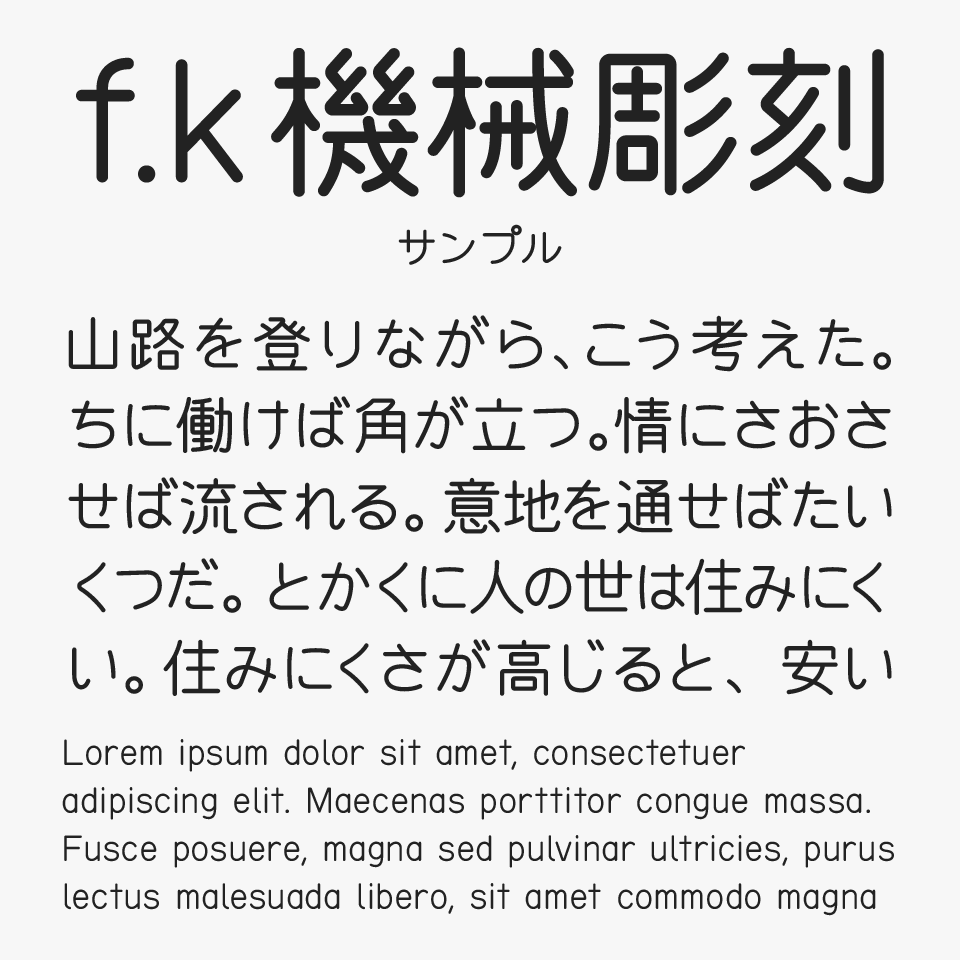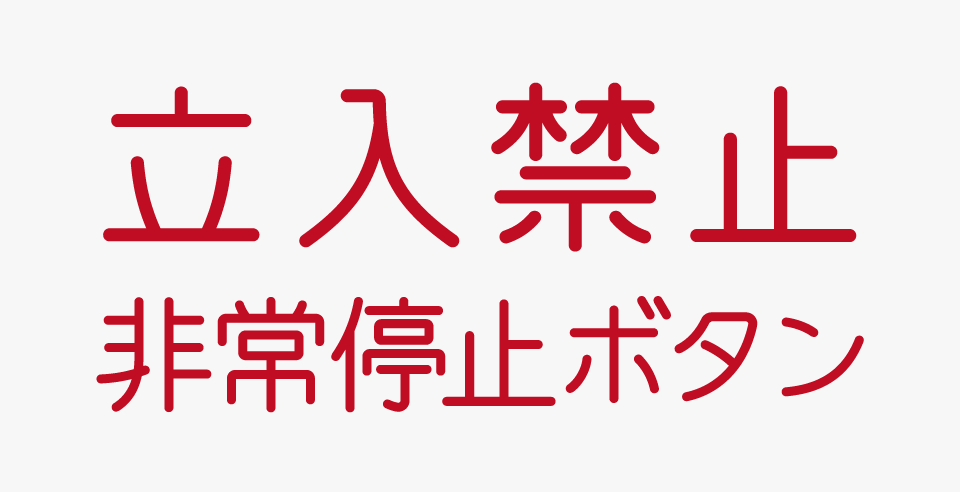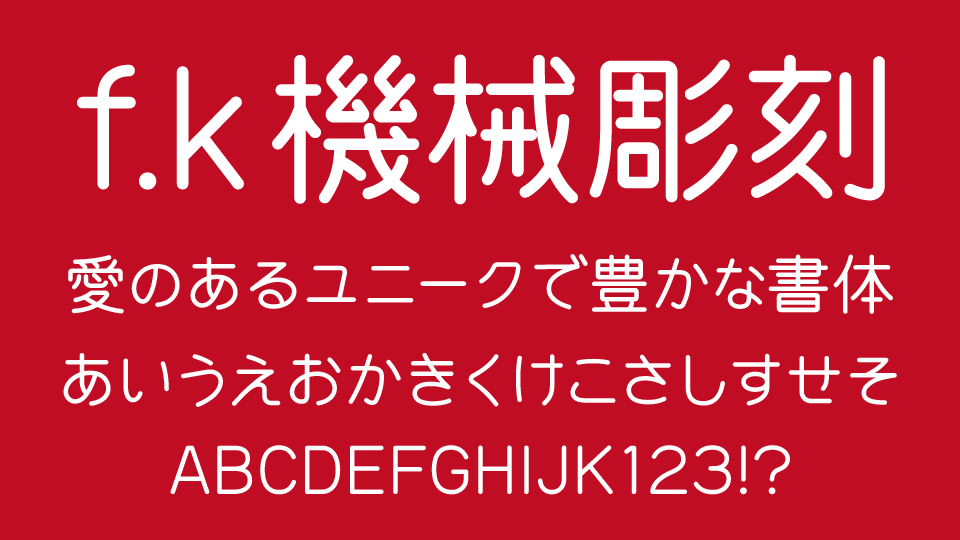
機械彫刻用標準書体(f.k 機械彫刻)フォントは、日本産業規格(JIS/旧日本工業規格)によって定められている、工業用途向けの標準書体をデジタルフォント化したフォントです。
均一で無駄のない線設計になっており、どこか無機質で工業的な雰囲気があるところが特徴のフォントです。視認性を重視して設計されているため、シンプルながら独特な存在感があり、インダストリアル系デザインやテクニカルなビジュアルとも相性の良いフォントとなっています。
駅のホームにある案内表示や看板、歩道橋、公共施設のサインなどにも多く使われている書体のため、意識していなくても、一度は目にしたことがある方も多いかもしれません。日常に溶け込んでいる“工業文字らしさ”を楽しめる、独特な魅力のあるフォントです。
工業的な彫刻文字として使われることを想定して設計されているため、文字の角はゆるやかな曲線になっており、ハネや筆押さえなども極力シンプルに整理されているところが特徴です。
これは、機械で金属やプレートへ文字を彫刻しやすくするための工夫で、複雑すぎない線構成によって、均一で安定した文字を刻めるように設計されています。(詳しい成り立ちについては、配布サイトでも丁寧に解説されています。)
駅の案内板や古い銘板、歩道橋、工場設備のプレートなどで、「どこか無機質だけど妙に味がある文字」を見かけたことはありませんか?
それこそが、「機械彫刻用標準書体(f.k 機械彫刻)」です。
「機械彫刻用標準書体(f.k 機械彫刻)」フォントを、ほかの丸ゴシックフォントと比較してみると、直線的で無駄を削ぎ落とした構成になっているのがわかりやすいです。(比較フォントは、キウイ丸、はこべら丸ゴシックA、新レトロ丸ゴシック、それぞれ違ったコンセプトの丸ゴシックなので、味わいあるので、あわせてチェックしてみてください。)